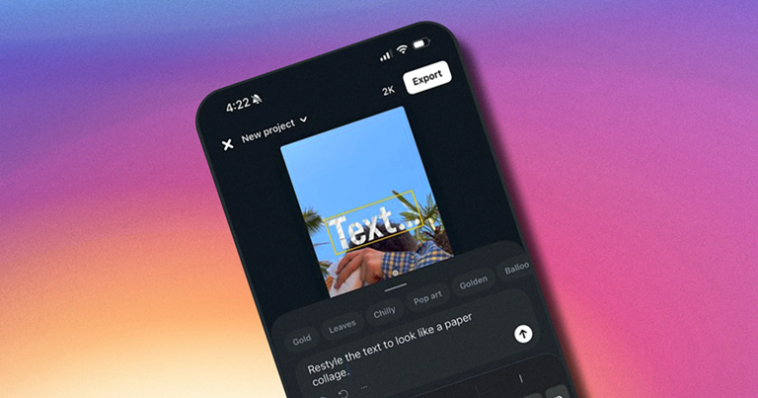
Meta-ს უახლესი ხელოვნური ინტელექტის ინსტრუმენტით შრიფტის დიზაინის შექმნა ჩვეულებრივი ტექსტური ბრძანების დაწერასავით მარტივი ხდება. კომპანიამ ფოტოებისა და მოკლე ვიდეოების დასამუშავებელ დამოუკიდებელ აპლიკაციაში, სახელად Edits, ახალი ფუნქციები ჩაუშვა. მათ შორისაა შრიფტებისთვის განკუთვნილი ხელოვნური ინტელექტის სტილი, რომელიც მომხმარებლებს ტექსტის დამოუკიდებლად მორგების საშუალებას აძლევს. ეს ფუნქცია Microsoft Word-ის კლასიკური WordArt-ის თანამედროვე ვერსიას წააგავს, ოღონდ ამ შემთხვევაში პროცესს ხელოვნური ინტელექტის ტექსტური ბრძანებები მართავს.
მისი პოვნა ტექსტის რედაქტირებისას, წერისა და შრიფტის არჩევის ღილაკებს შორის მოთავსებული სტილის შეცვლის ხატულაზე დაჭერით მარტივადაა შესაძლებელი. შეთავაზებული ბრძანებების სია ნათლად აჩვენებს ხელმისაწვდომ შესაძლებლობებს, ხოლო ჩატვირთვის ეკრანზე ანიმირებული პლუს ნიშნების პატერნი ჩნდება. მაგალითად, პოპ-არტის სტილის არჩევისას ბრძანების ველი უფრო დეტალური ინსტრუქციებით ივსება, რომელიც კომიქსების მსგავსი შრიფტის, პოსტერისებრი ჩრდილების, მკვეთრი ფერების, სქელი კონტურებისა და ასოებიდან გამომავალი დიდი ფორმების შექმნას ითვალისწინებს, ფონზე კი აფეთქების ეფექტით. შედეგად, ტექსტი მართლაც ზუსტად ისეთია, როგორიც კომიქსებში გვხვდება. ტყის თემატიკის არჩევისას კი იქმნება ტექსტის სტილი, სადაც ასოებიდან ტოტები, ფოთლები და უამრავი თეთრი, იისფერი და ყვითელი მინდვრის ყვავილი ამოიზრდება.
საკუთარი პრომპტის დაწერისას მიღებული შედეგი ხშირად იმაზე უკეთესია, ვიდრე ველოდებით, თუმცა სისტემა სრულყოფილი მაინც არ არის. ზოგჯერ გენერატორს მარტივი ინსტრუქციების გაგებაც უჭირს და სასურველი შედეგის მისაღებად რამდენიმე მცდელობა ხდება საჭირო. სწორედ ამიტომ, წინასწარ გამზადებული პარამეტრები ყველაზე ეფექტურად მუშაობს.
მართალია, შრიფტებისთვის განკუთვნილი ხელოვნური ინტელექტის სტილი ჯერ კიდევ დასახვეწია, მაგრამ ის მკვეთრად ზრდის კრეატორებისთვის ტექსტის მორგების შესაძლებლობებს და ნათლად აჩვენებს ტექნოლოგიური პროგრესის მასშტაბებს. ზუსტად ისე, როგორც ხელოვნურმა ინტელექტმა რეალისტური ხელების დახატვა ისწავლა, მან უკვე მკაფიო და მარტივად წასაკითხი ტიპოგრაფიის შექმნაც შესანიშნავად აითვისა.